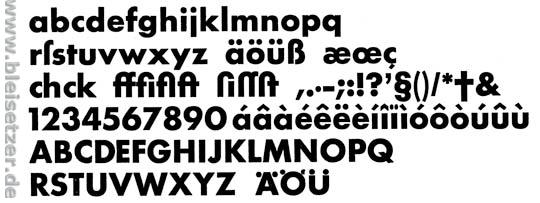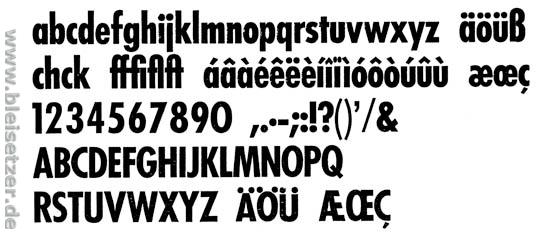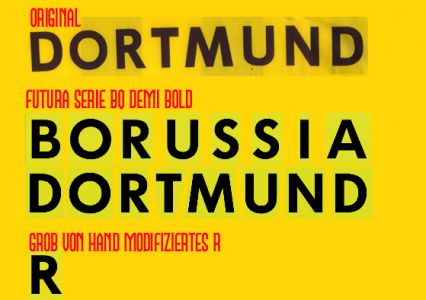
Dortmund-Schriftzug, wahrscheinlich kein "Custom"-
Hallo Typo-Experten, ich suche schon seit langer Zeit den Namen dieses Fonts, bislang leider ohne Erfolg. Ich habe auch den Hersteller des Trikots angemailt, er kann mir ebenfalls nicht weiterhelfen. Alles, woran er sich erinnert, ist folgendes : Er geht davon aus, daß es sich um irgendeinen Standardfont handelt, da es bei diesem Hemd keinen Auftrag für eine "typografische Sonderanfertigung" gegeben hat. Kann mir jemand weiterhelfen ?
Das ist die Futura fett.
Der Schriftzug im Label läuft schmaler, richtig?
Das M und das R sind etwas anders, glaube ich?
Unten nun die schmalfette Futura.
Ich versteh jetzt deine Antwort nicht ganz.
Futura dachte ich auch auf den ersten Blick, aber das ›R‹ sah mir dann doch etwas verdächtig aus. Außerdem wirkt das ›T‹ etwas unausgewogen als wäre es einfach geometrisch mit gleichen Stärken für horizontal und vertikal gezeichnet worden — die Futura kann das ja besser.
Ist das nun eine Futura die von den verbreiteten Varianten abweicht?
Das R ist irgendwie eher wie bei der Akzidenz Grotesk, aber die Century Gothic ist es wohl auch nicht, oder?
Eine Futura ist eine Futura.
Das hier gibt es doch gar nicht.
"Ist das nun eine Futura die von den verbreiteten Varianten abweicht?"
Entweder ist es eine Futura oder es ist keine.
Dies ist keine.
Warum nicht, weiß ich nicht.
Ich als Setzer, der sich nur mit Kack-Bleisatz auskennt, wollte Euch Fachleuten der modernen Fonttechniken und der ungemein effizienten Möglichkeiten zur Modifikation nur die direkte Gegenüberstellung des Schriftzuges mit den in Frage kommenden Futura-Schnitten ermöglichen.
Jetzt habt Ihr was an der Hand und könnt entscheiden.
Ich setze weder blei noch modifiziere ich effizient. Wenn das hier ein Zwei-Parteien-System wird, sagt Bescheid, dann gehe ich rechtzeitig in die Opposition (von mir aus auch außerparlamentarisch).
Ansonsten sieht das mit den ganzen "falschen" Ts und Rs auch irgendwie nachAufbügelbuchstaben aus, so wie sie mir meine Mami in den Siebzigern aufs T-Shirt geplättet hat.
Hmmm. Und eine Garamond ist eine Garamond, gell?
Es gibt ja von einigen Klassikern herb unterschiedliche Varianten, und auch die Futuras werden ja wohl nicht alle gleich sein; ich bin aber zu wenig Futura-Experte um zu wissen ob es einen so krassen Ausreißer — wie bei der Garamond die ITC — gibt.
Diesbezüglich habe ich deinen Satz »Das ist die Futura fett« so verstanden, als wenn du den Schriftzug als solche erkannt zu haben glaubtest.
Ich hoffe die ›Blei-Kacke‹ liegt dir nicht zu sehr im Magen, ich bin mir sicher, dass das nicht so heiß gegessen werden sollte wie hier serviert. Ich muss allerdings auch anmerken, dass das Thema Bleisatz in der jüngsten Zeit schon etwas überproportional breit getreten wurde in Anbetracht dessen, dass es wohl kein Promille der professionell mit Schriften arbeitenden Menschheit ist die noch dieses Handwerk pflegen.
Vielleicht ist der Ausdruck ›Blei-Kacke‹ ja auch dem zu danken, dass man als geneigter Leser den Eindruck haben konnte, dass der eine oder andere der Bleihandwerker unser digitales Handwerk von einem sehr hohen Ross (oder Kamel) aus beurteilte.
Dies bitte jetzt nicht falsch zu verstehen: zum Einen habe ich Vieles dessen, was die Herren Bleisetzer und Bleisatzkundigen hier geschrieben habe mit Interesse gelesen und zum Anderen hatte ich auch bei dir, Georg, niemals den Eindruck der Überheblichkeit.
Lieber Markus,
der Begriff "Bleisatz-Kacke" ist mir rausgerutscht, weil ich heute aus privaten Gründen sau-schlechte Laune habe. Und bestimmt nicht, um Sharifs Bemerkung aufzufrischen und daraus nun einen Streit vom Zaun zu brechen.
Was Du mit dem Schwerpunkt der letzten Wochen meinst und wie Du ihn ganz objektiv beschreibst, ist auch für mich einleuchtend. Aber das hat sich ja nun erledigt. Ich glaube, ich bin nun der einzige noch aktive Bleisetzer hier. Und ich, das weißt Du, gehe Euch höchstens mit meinem preußischen Gedankengut auf die Nerven - das dann aber auch mit höchster Penentranz.
Ein klein wenig anders beurteile ich Herkunft von klassischen Schriften. Bei Fragen zu digitalisierten Schriften halte ich mich raus. Davon weiß ich nichts und lese mit Interesse mit, versuche zu verstehen und wichtiges zu behalten.
Geht es aber um klassischen Schriften - die nun einmal (aber dafür kann niemand etwas) aus der Bleisatz-Zeit kommen, dann schreibe ich gern etwas dazu. Lege sogar wert darauf, Informationen zu geben, die Euch nicht wirklich interessieren (z.B. Erstguß-Jahr oder Schriftgießerei).
Was Du zur Garamond sagst, ist falsch. (Gleich Falsches hättest Du auch zur Bodoni sagen können).
Beides sind Schriften, die in mit Erfindung des industriellen Weges zur Produktion beweglicher Lettern (ich will mich vor dem Reizwort "Schriftgießerei" drücken, merxt Du's?) nicht 1:1 umgesetzt, sondern interpretiert wurden.
Warum muß es für alles eine Laienversion und eine Profiversion geben ?!?!
O.k., genug geheult. Wenn einige von Euch, die mir mit Rat und Tat zur Seite gestanden haben nun verärgert sind, daß es sich bei meinem "Problem" nicht um die Erledigung eines Jobs handelt, weil dieses Forum villeicht dafür gedacht war, einander bei beruflichen Problemen zu helfen, möchte ich mich gerne dafür entschuldigen. Von mir aus ist das Thema erledigt. Sollte aber doch noch jemand über diesen Freefont stolpern, würde ich mich über eine neue Antwort sehr freuen.